商用利用OK!かわいい英語フォントバンドルを無料ダウンロード【約400ドル相当】
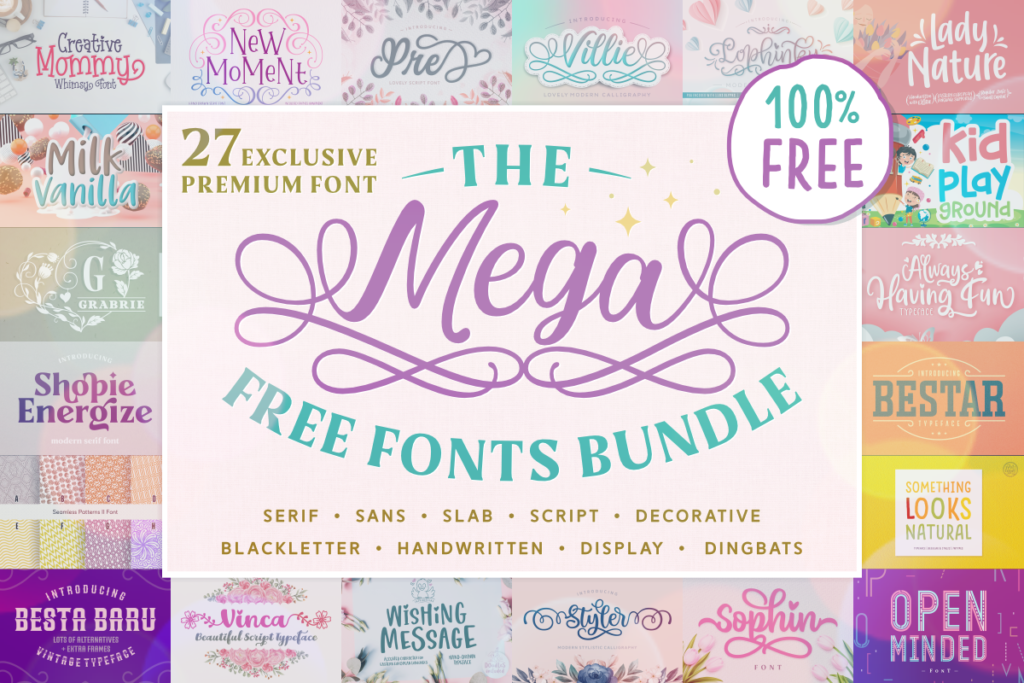
Creative Fabricaでは英語フォントバンドル「The Mega Free Fonts Bundle」が無料配布中です。
- 総額400ドル以上相当の英語手書きフォントやパターン素材などを収録
収録データからおすすめ素材をピックアップ